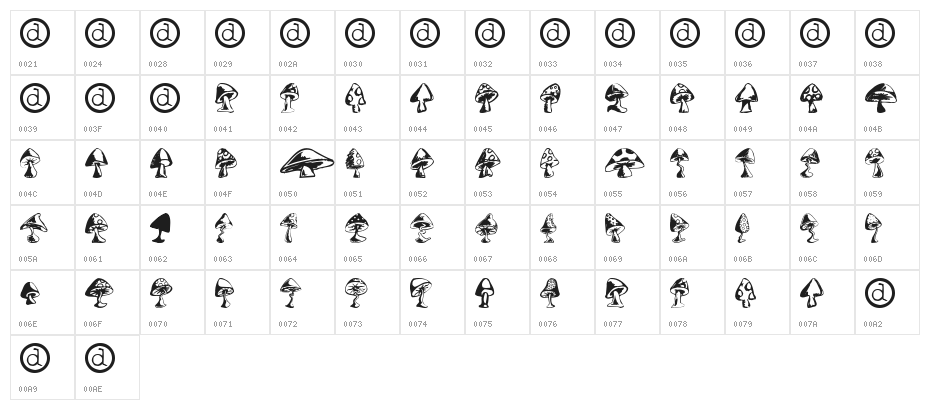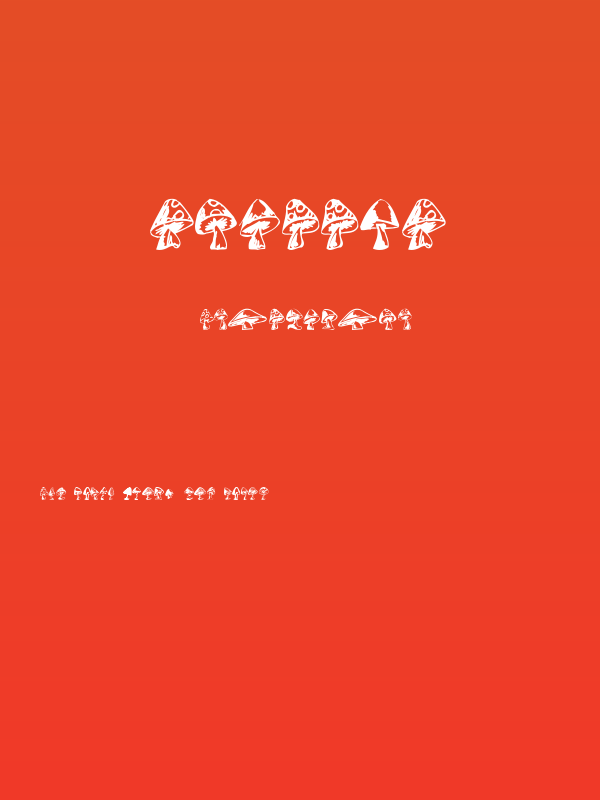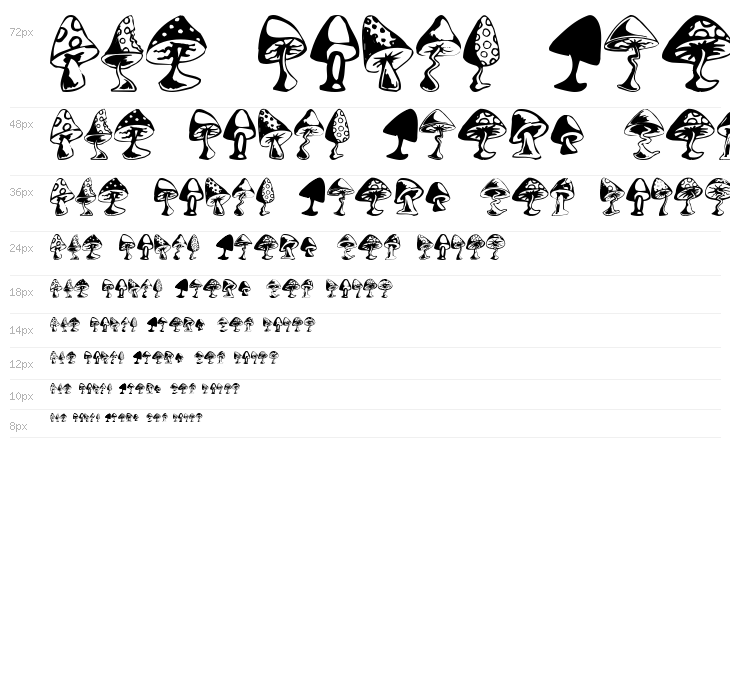
Shrooms Font
| Gesamtstil | Whimsical, Playful, Hand-drawn |
| Anwendungsfall | Logos, Posters, Creative Branding |
| Vorgeschlagene Projekte | Ideal for children's books, fantasy-themed designs, posters, and creative branding projects. |